Las fuentes sans-serif en negrita redefinen su papel en la tipografía, desafiando la noción de que solo son adecuadas para aportar simplicidad y juventud. Lejos de ser simplistas, las versiones más audaces de las fuentes sans-serif ofrecen a los diseñadores tipográficos un lienzo para celebrar el carácter inherente de la fuente. Es en estas versiones más pesadas donde brilla el arte del diseño tipográfico, transformando lo que podría ser sencillo en algo con personalidad.
Por ejemplo, considere los matices sutiles que se pueden amplificar en fuentes sans en negrita: las barras horizontales centrales que son muy claras en comparación con sus contrapartes más gruesas en la parte superior e inferior, o los cuencos de letras como 'o', 'b' y 'd', que pueden adoptar una forma ligeramente cuadrada, presentando un toque aún más juvenil y divertido. Los extremos pueden terminar en trazos similares a pinceladas, lo que le da una calidad dinámica, casi manuscrita , al tipo de letra. Estas elecciones de diseño deliberadas enfatizan los rasgos de la familia de fuentes, haciendo que los pesos en negrita no solo sean más fuertes sino más articulados.
Los diseños modernos de fuentes sans-serif en negrita cuestionan la concepción tradicional de las fuentes sans como la encarnación del minimalismo . Con trazos rectos que dan paso a formas más divertidas y atractivas, estas fuentes dan la bienvenida a un carácter más divertido y accesible. Esto no debilita su impacto, sino que mejora su accesibilidad, lo que ayuda a los diseñadores a agregar carácter de una manera fuerte y significativa.
A nuestro estudio tipográfico le encanta la versatilidad de las fuentes sans serif en negrita. A continuación, hemos creado una colección de diez fuentes sans serif en negrita que son tan agradables como llamativas. Estas fuentes son testimonio de la idea de que las fuentes sans serif pueden ser sobrias y animadas.
1. Bool, juguetón en negrita con contadores desplazados
Bool, fuente divertida en negrita con barras centrales horizontales más delgadas y puntas puntiagudas.
2. Mosy, fuente sans-serif ancha y moderna con la letra S invertida
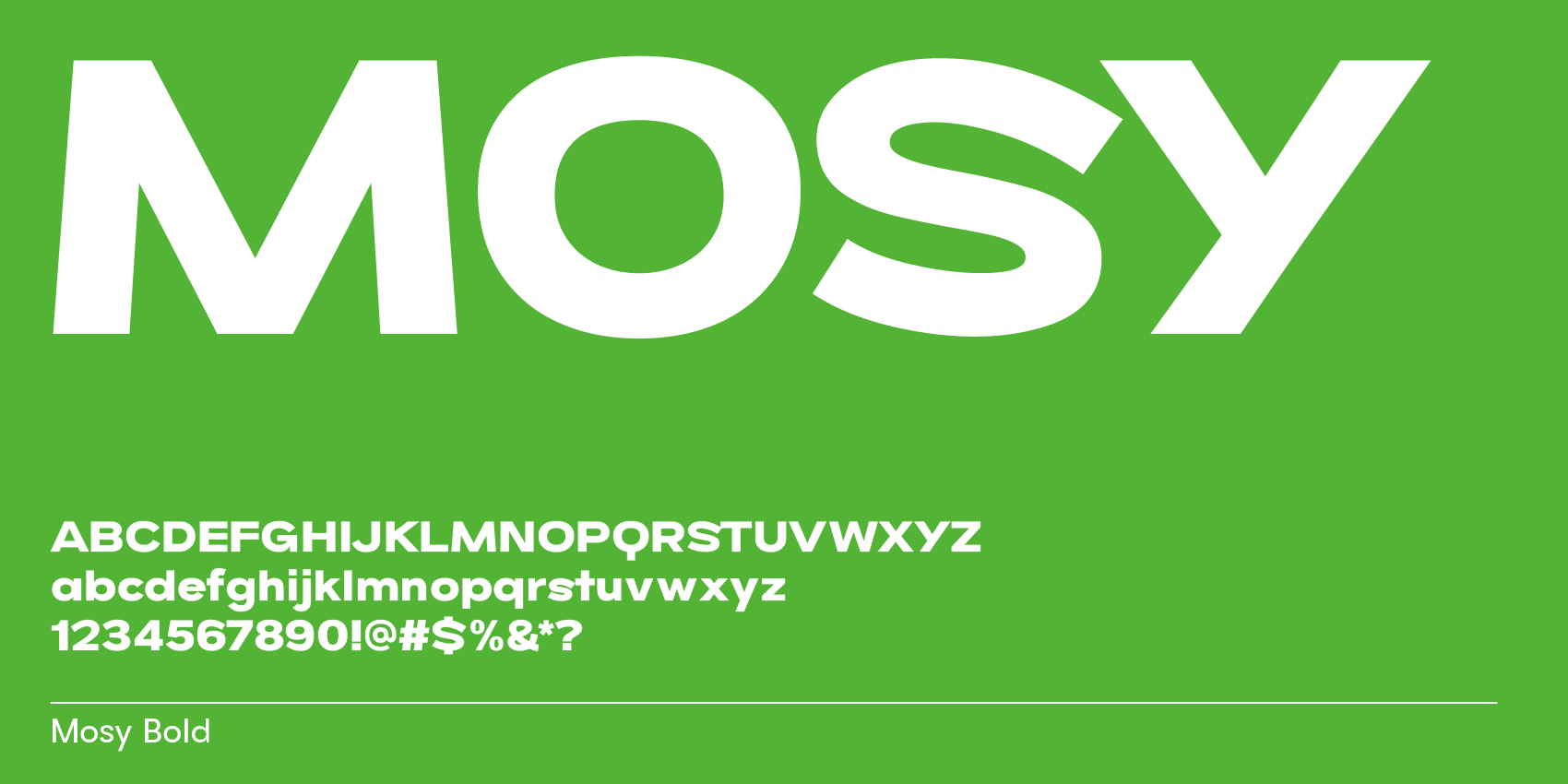
Mosy en Bold, Extrabold y Black. Fuente sans-serif moderna con S y 8 invertidos para una apariencia divertida.
3. Goji, clásica fuente sans redondeada con marco geométrico para una sensación suave en negrita.
Goji, fuente sans-serif clásica y redondeada similar a las fuentes Crocs y Hello Kitty.
4. Apex, fuente sans-serif para todo tipo de herramientas: puntas afiladas
Bauhaus Apex con puntas puntiagudas para glifos de ápice y vértice.
5. Chez, fuente sans de contraste redondeado para una sensación suave en pesos más audaces
Aquí, amigable contraste sin fuente.
6. Vole, mostradores rellenos sin para un aspecto acuoso en negrita
Bauhaus Vole, fuente de agua.
7. Anky, fuente sans estilo Helvética para un diseño clásico y audaz
Anky, similar a Helvética en estilo.
8. Byrl, tipografía sans-serif ancha para una apariencia moderna y delgada de trampa de tinta
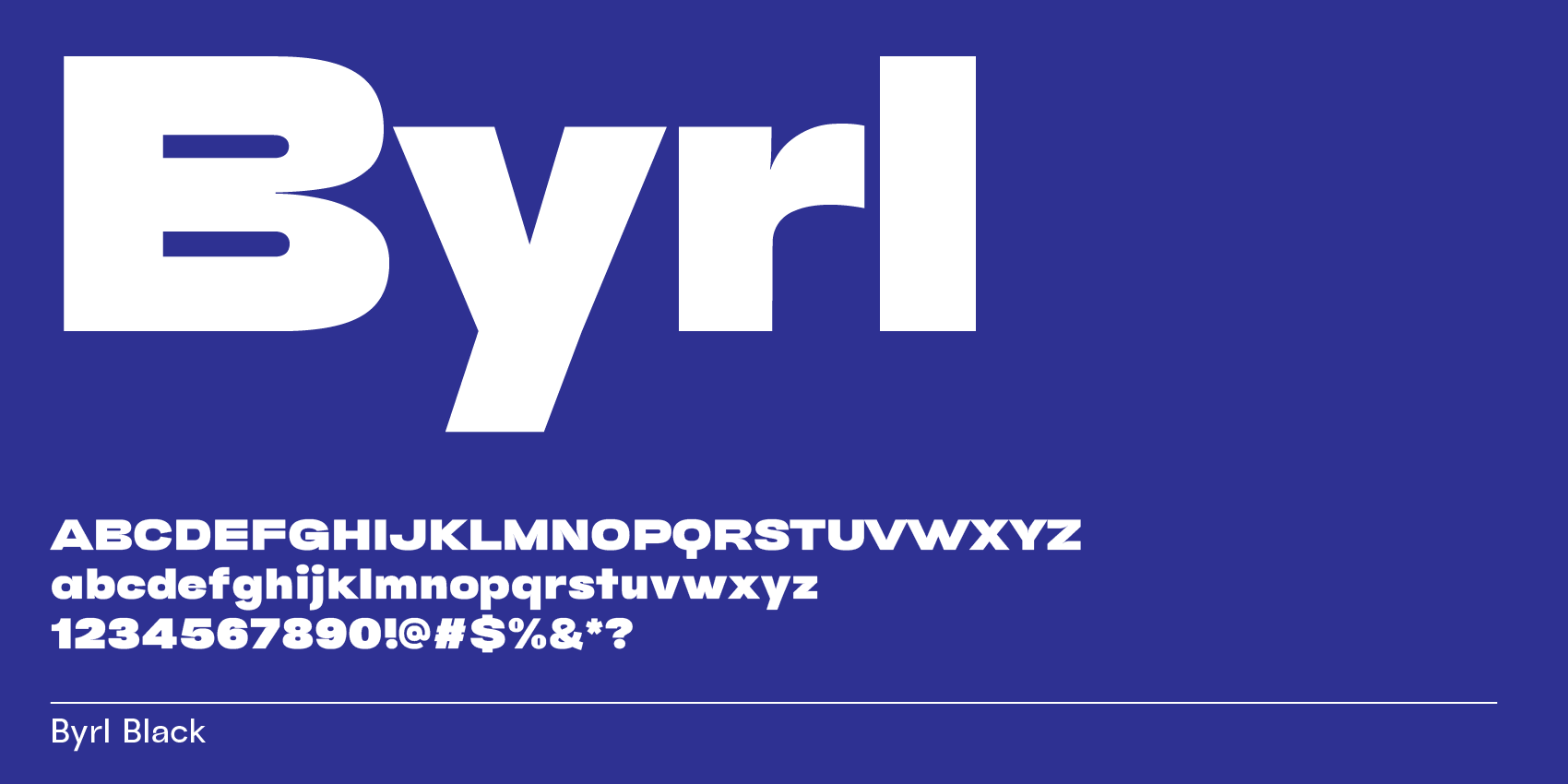
Byrl Negro.